NEW 80s MATERIAL 80年代的イラスト素材集
「NEW 80s MATERIAL 80年代的イラスト素材集」が翔泳社から2018年3月5日に発売される。
「すべてが、エイティーズになる?!」をキャッチコピーに、いち、いちかわあすか、F*Kaori、m7kenji、神保賢志、鈴木旬、電Q、中根ゆたか等のクリエイターがイラストを手掛け、80年代グラフィックを現代にアップデートした作風を軸に活躍するステレオテニスが監修した素材集。人気クリエイターが描く「今」の80年代ヴィジュアルをモチーフに雑貨・フード・植物・季節モチーフ・感情・フォント・パターンを素材化している。
すべてがエイティーズになる!? 80年代グラフィックを現代にアップデートした作風を軸に活躍するステレオテニスが監修を務め、いち、いちかわあすか、F*Kaori、m7kenji、神保賢志、鈴木旬、電Q、中根ゆたから第一線で活躍するクリエイターが手掛けるイラスト素材集。それぞれのクリエイターが考える、「今」の80年代的ビジュアルイメージを集めました。生活雑貨などのアイテムをはじめとする暮らしのシーン・モノ、12か月の行事、季節モチーフや人物や動物のイラストなど、身の回りのあらゆるモノ・コトを80年代風に表現。丸文字フォントやパターン、飾り罫線、装飾フレームなど、デザイン素材も掲載しています。懐かしいのに新しい、エイティーズワールドを人気クリエイターの作品集としても楽しめる一冊です。
'80sガーリー雑誌広告コレクション
奇しくも2018年3月8日には、漫画、アイドル、映画、音楽など1970~80年代の昭和ガーリーカルチャーを懐古&発信する「昭和的ガーリー文化研究所」所長であるゆかしなもん著書の1980年代の懐かしガーリー雑誌広告200点超掲載した「'80sガーリー雑誌広告コレクション」がグラフィックス社から発売される。
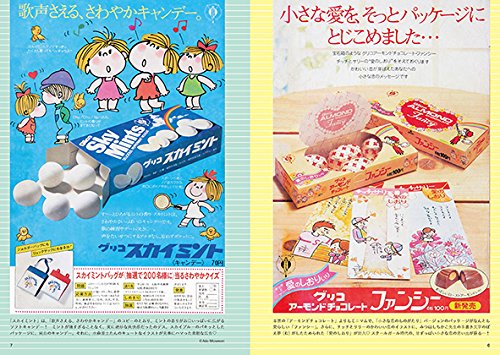
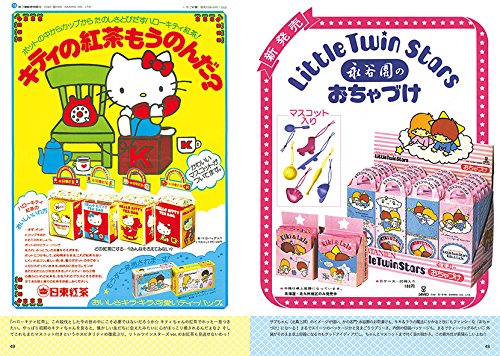
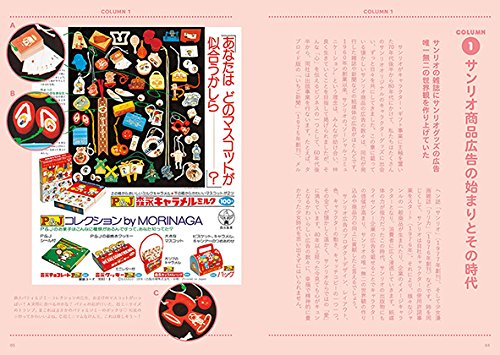
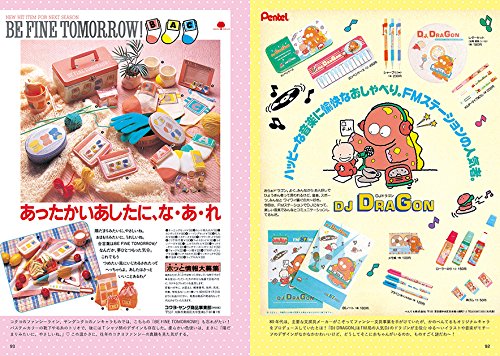
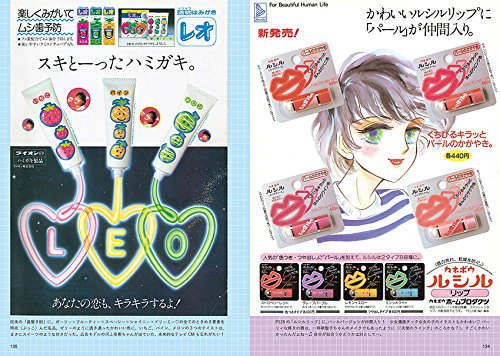
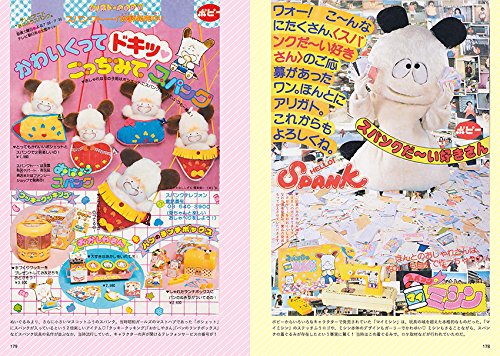
1980年代の懐かしガーリー雑誌広告200点超掲載! 著者・ゆかしなもんが当時実際に読んでいた少女漫画誌、ティーンファッション誌から、特に思い入れのある可愛い広告をセレクト! 「お菓子」「玩具」「コスメ」「ファッション」「サンリオ」などのカテゴリ別に収録します。あなたの思い出の広告はありますか?
ゆかしなもんProfile●1975年愛知県生まれ。文具、玩具、漫画、アイドル、映画、音楽など1970?80年代の昭和ガーリーカルチャーを懐古&発信する「昭和的ガーリー文化研究所」所長。2010年より同名の武露愚(ブログ)をスタート。2012年と2014年にイベント「ゆかしなEXPO」開催。2017年、ヴィレッジヴァンガード限定80'sキャラコラボ商品をプロデュース(うちのタマ知りませんか?、レッツチャット、バイキンクン)。同年、自身の1500点を超えるコレクションから選りすぐりのアイテムを展示した「'80sガーリーコレクション~"カワイイ"は時間を超える~展」(宝塚市立手塚治虫記念館)監修。
'80sガーリーコレクションシリーズ第1弾「'80sガーリーデザインコレクション」
また'80sガーリーコレクションシリーズ第1弾として、ゆかしなもん著書による「'80sガーリーデザインコレクション」が2017年3月8日にグラフィック社から発売されている。
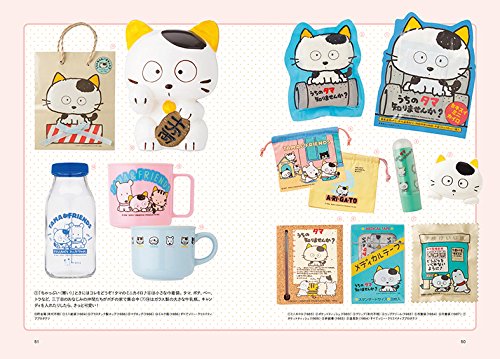
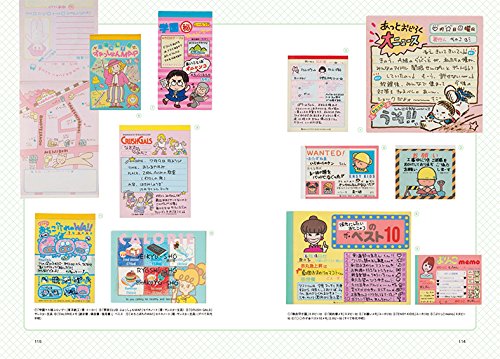
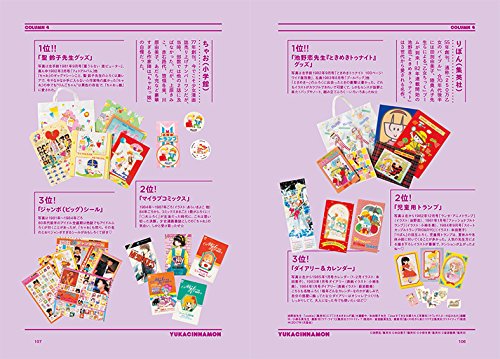
1970~80年代の昭和ガーリーカルチャーを懐古&発信する「昭和的ガーリー文化研究所」所長・ゆかしなもんの貴重なお宝を大公開! 1300点以上にも及ぶ懐かしのファンシーグッズを収録します。